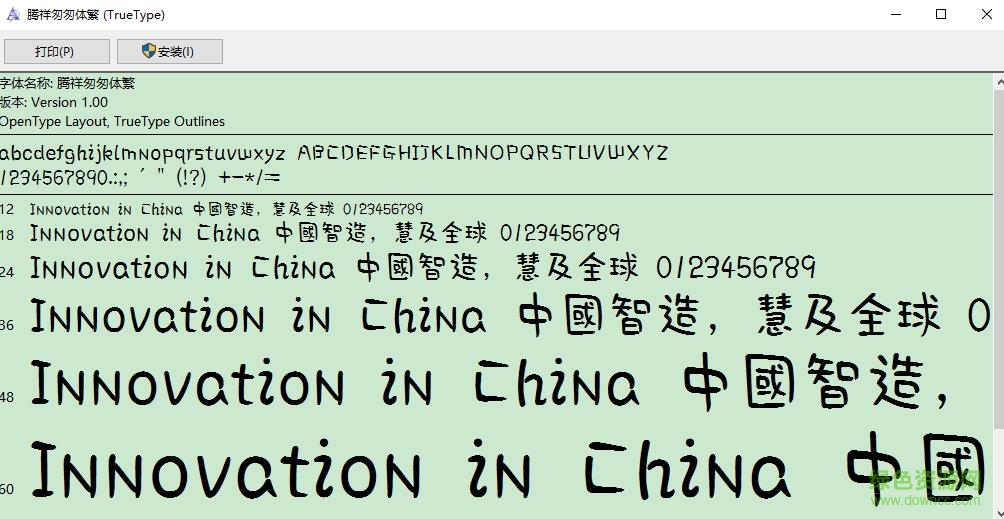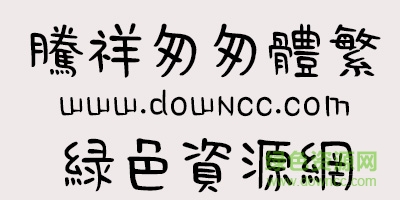
騰祥匆匆體繁字體是一款非常有特色的繁體字體,這款可以應(yīng)用于美工設(shè)計(jì)、海報(bào)廣告等方面,喜歡的朋友歡迎來(lái)綠色資源網(wǎng)下載使用!
騰祥匆匆體繁字體雖是一款繁體字體,但是還是很實(shí)用的,整體效果非常出色,大家可以用在很多方面,喜歡的朋友可以來(lái)綠色資源網(wǎng)下載。